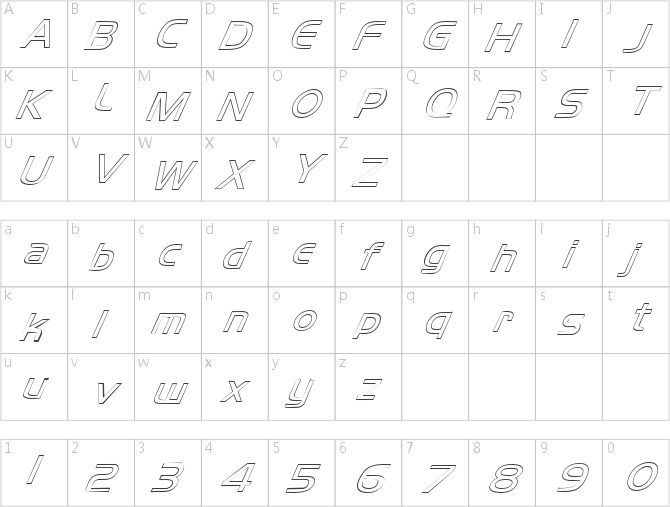
FZ BASIC 8 HOLLOW ITALIC
FZ BASIC 8 HOLLOW ITALIC介紹
FZ BASIC 8 HOLLOW ITALIC字體字庫是一款讓人賞心悅目、百看不厭的英文字體,適合各類廣告和產品包裝設計應用,字體大小0.07MB,格式為ttf字體,上傳用戶是Bot,作者/版權方為未知